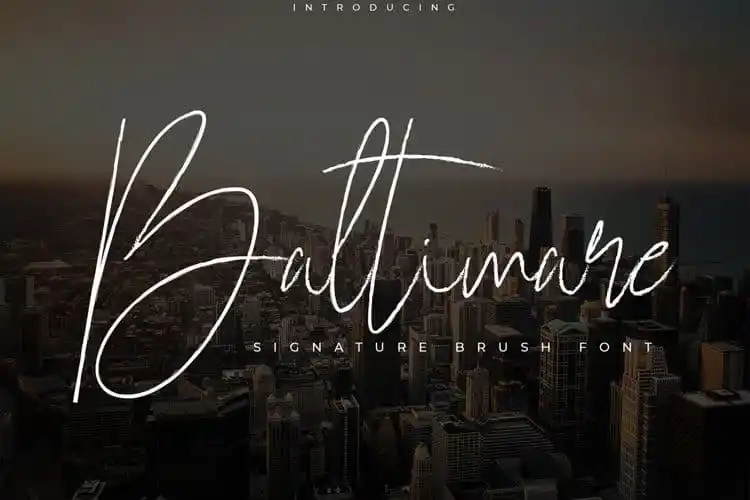
Baltimare Brush Font – Download Grátis
A Fonte Baltimare Brush é uma opção atraente para quem busca criar designs únicos e envolventes com estilos manuscritos. Criada por jadatype, esta fonte vem ao encontro de um estilo brush que oferece uma impressão elegante mesmo em linhas finas e delicadas. Seu design é ideal para nomear produtos, logotipos e ambientes digitais como redes sociais, bem como para estilos de marca, nomes de livros, sinopses cinematográficas ou qualquer outro tipo de design que você possa imaginar. Com uma ampla gama de letras em inglês padrão e algumas letras multilingue, esta fonte é fácil de instalar nas ferramentas de criação como o Illustrator, Photoshop ou até mesmo no Microsoft Word. A Fonte Baltimare Brush é perfeita para quem deseja adicionar personalidade e sofisticação a seus projetos digitais. Suas linhas elegantes são adaptáveis aos diversos usos do design gráfico, tornando-a uma excelente opção quando se trata de criar nomes memoráveis para produtos ou marcas. Além disso, sua facilidade na instalação é um benefício adicional para quem deseja implementar esta bela fonte em seu dia a dia de trabalho com ferramentas digitais. Não importa o tipo de projeto que você está enfrentando, a Fonte Baltimare Brush tem o poder de torná-lo único e profissional, sem dúvida uma escolha valiosa em qualquer projeto gráfico criativo.